그중에서 눈누 폰트는 상업적으로 이용할 수 있는 무료 한글 글씨체를 모아 놓은 유명한 사이트입니다.
이 포스팅에서는 파워포인트 폰트에 추가하기 위해 눈누 폰트 사용법을 알려드리겠습니다.
눈누 폰트 사이트의 좋은 점
눈누 사이트는 상업용 무료 한글 글씨체를 모아 놓고 정리해 놓은 아주 유용한 사이트입니다.
이 사이트의 좋은 점 3가지를 정리해 보았습니다.
1. 내가 원하는 목적과 스타일에 따라서 검색이 쉬움
내가 원하는 용도나, 스타일을 체크하면 수많은 폰트를 한눈에 볼 수 있습니다.
2. 직접 문구를 입력한 후 미리 보기 가능
이런 기능은 로고를 제작하거나 카피라이터를 작업할 때 미리 어울리는 폰트를 찾기 위해서 유용하게 사용할 수 있습니다.
3. 다른 사람이 상업용 무료 글씨체로 만든 다양한 디자인을 볼 수 있음
내가 디자인하려는 이미지와 비슷한 포트폴리오를 보면서 다른 사람의 폰트 사용 방법을 참고해 볼 수 있습니다.
눈누 폰트 다운로드 방법
2. 눈누 사이트 둘러보기
사이트를 전체적으로 한 번 둘러보시고, 마음에 드는 글씨체가 있다면 선택해서 보면 될 것 같습니다.
1) 추천 폰트
맨 처음 접속하면 보이는 곳인데 자주 사용되는 것 보다 최근 개발된 글씨체들 위주로 정렬된 것 같습니다.
2) 모든 폰트
눈누 폰트 사이트에서 상업적으로 사용할 수 있는 모든 폰트가 있는 곳입니다.
- 폰트 검색 : 직접 폰트를 검색하여 찾기 가능
- 예시 문구 적기 : 원하는 문구를 적어 미리 보기 가능
- 픽셀 슬라이드 : 글자 크기 조절 가능
- 허용 범위 : 사용 목적에 맞는 폰트 필터링 가능
- 폰트 형태 : 원하는 글씨체로 필터링 가능
- 정렬 방식 : 인기순, 조회순, 최신순, 이름순으로 정렬 가능
3) 무슨 폰트?
어떤 폰트인지 궁금한 것을 질문하고 답변하는 커뮤니티 기능입니다.
4) 디자인 공유
사람들이 눈누 사이트에 있는 상업용 무료 글씨체를 사용해서 만든 다양한 디자인을 공유하는 곳입니다.
디자인에 사용된 글씨체도 나타나 있기 때문에 다른 디자이너의 폰트 사용 방법을 참고할 수 있습니다.
3. 폰트 선택 후 다운로드
1) 원하는 폰트 필터링하기
폰트의 종류가 다양하고 많기 때문에 필터링을 해주겠습니다.
저는 무료 폰트에서 웹사이트, 손 글씨, 인기순으로 필터링했습니다.
2) 예시 문구 작성하여 미리 보기
예시 문구를 “파워포인트 폰트 바꾸기”로 적용해 보았습니다.
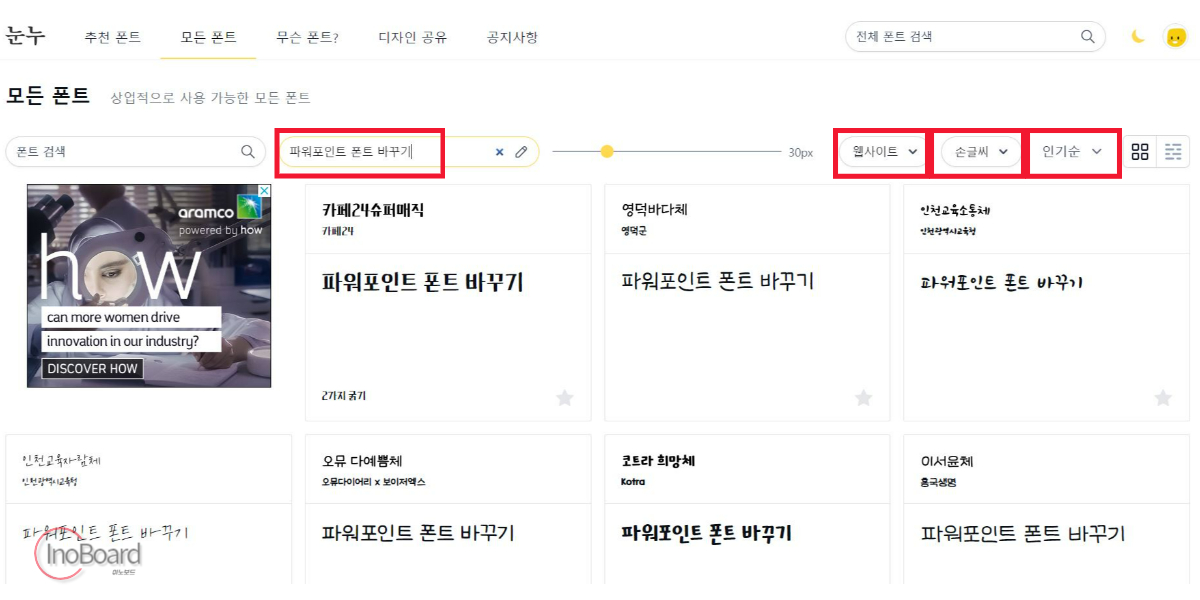
3) 원하는 폰트 선택하기
여러 가지 글씨체 중 마음에 드는 폰트를 선택하시면 됩니다.
저는 가장 앞에 있는 “카페24슈퍼매직” 글씨체를 선택하겠습니다.
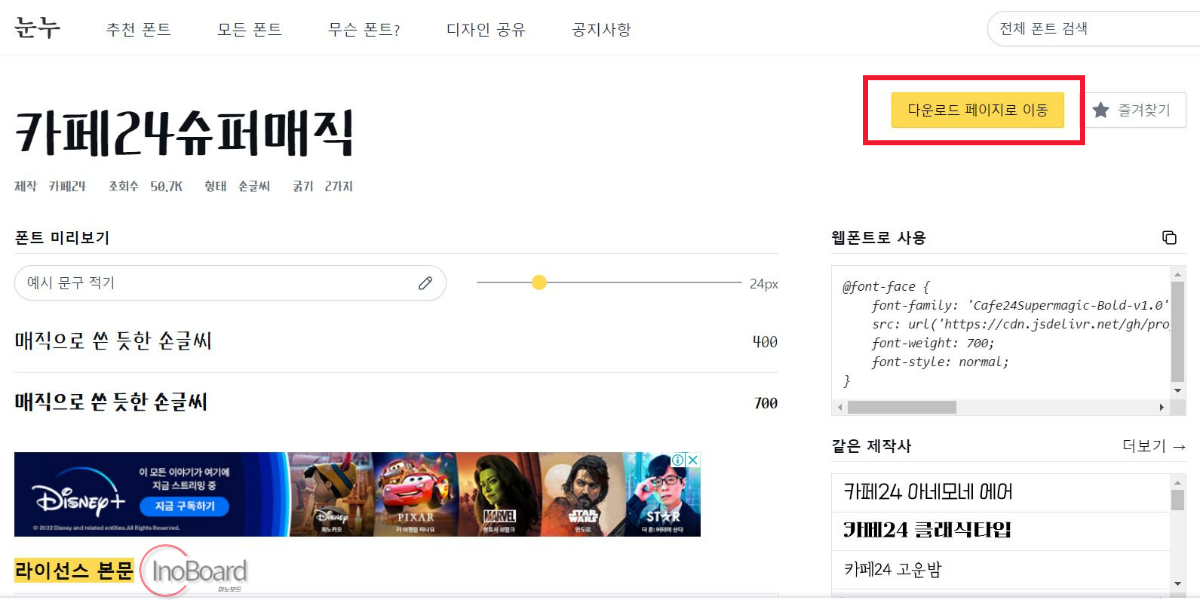
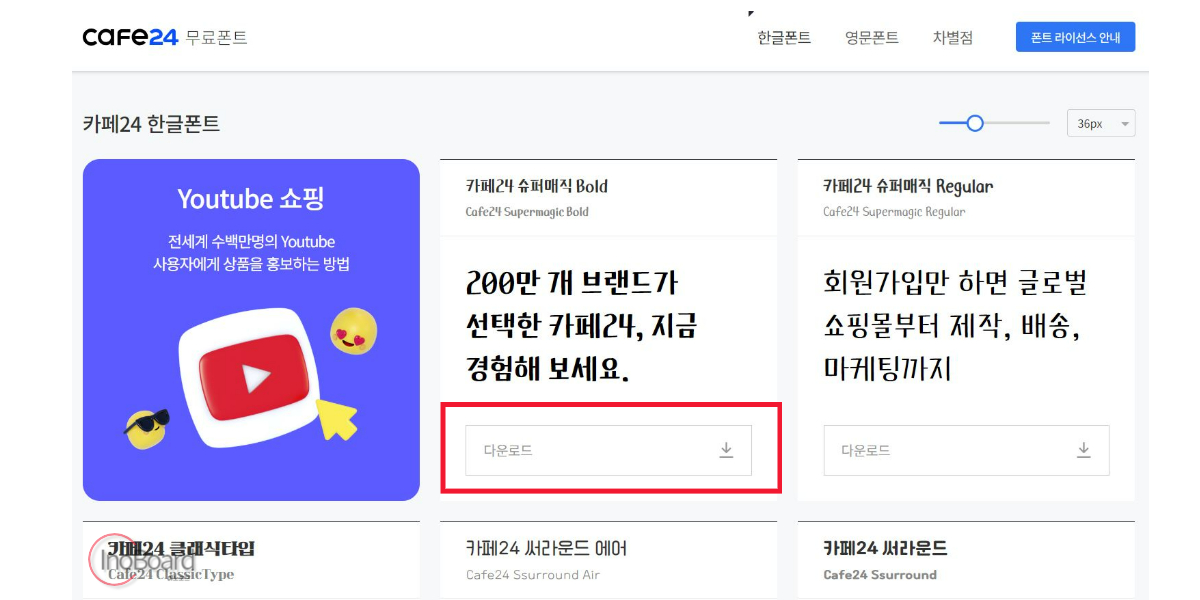
눈누 폰트 사용법
눈누 폰트 다운로드한 글씨체를 파워포인트 폰트에 적용해 보겠습니다.
3) 파워포인트에서 텍스트를 입력하고 다운로드 한 폰트로 변경
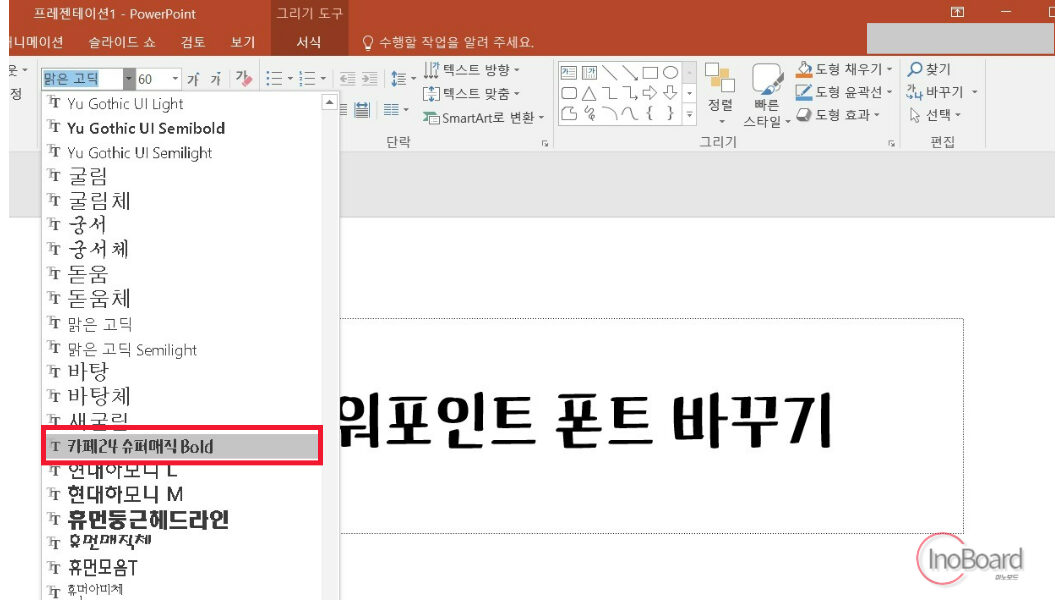
다운로드 한 “카페24슈퍼매직” 폰트가 설치되고 적용할 수 있습니다.
디자인 목적 사용 시 추천하는 폰트
1. 에스코어 드림
- 일반적인 고딕체로 어디에나 잘 어울리는 깔끔한 폰트
- 굵기가 다양해서 디자인적인 느낌을 표현하기 좋음
- 총 9개의 굵기가 있어 용도나 상황에 맞게 변형이 가능함
2. 여기어때 잘난체
- 강조하고 싶은 부분이나 메인 타이틀에 어울리는 적합한 폰트
- 딱딱한 느낌보다 부드러운 느낌으로 강조할 때 사용
- 계절에 맞춰서 사용하기에도 잘 어울리는 글씨체
3. 조선일보명조체
- 전문적이고 감성적인 느낌으로 강조하고 싶을 때 사용하는 폰트
- 볼드 처리 전과 후를 적절하게 사용하면 어디서나 유용하게 사용 가능
4. 잉크립퀴드체
- 부드러운 손 글씨 느낌을 주고 싶을 때 사용
- 아기자기하면서 여성스러운 느낌 또는 부드러운 느낌을 표현할 때 사용
5. 카페24 아네모네
- 비스듬하게 각진 폰트가 타이틀이나 강조하고 싶은 문구를 표현할 때 적절함
- 남성적이면서 강조하고 싶은 부분을 보여줄 때 사용할 수 있음